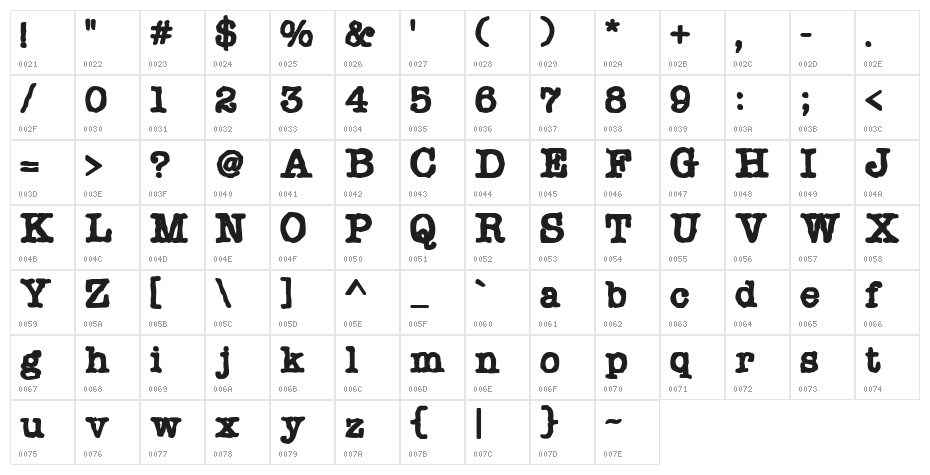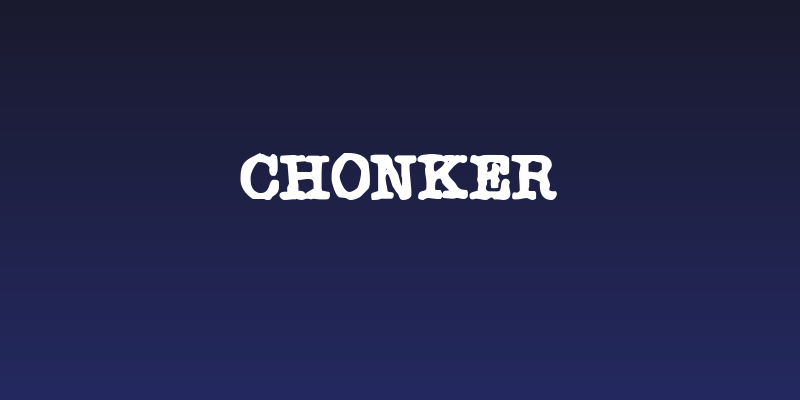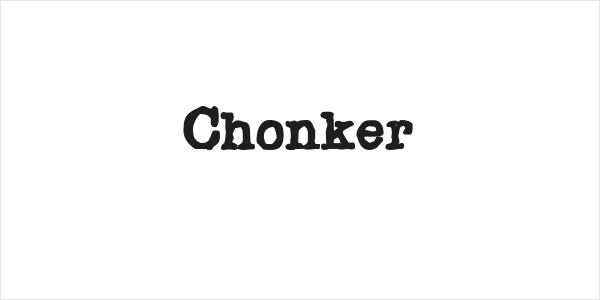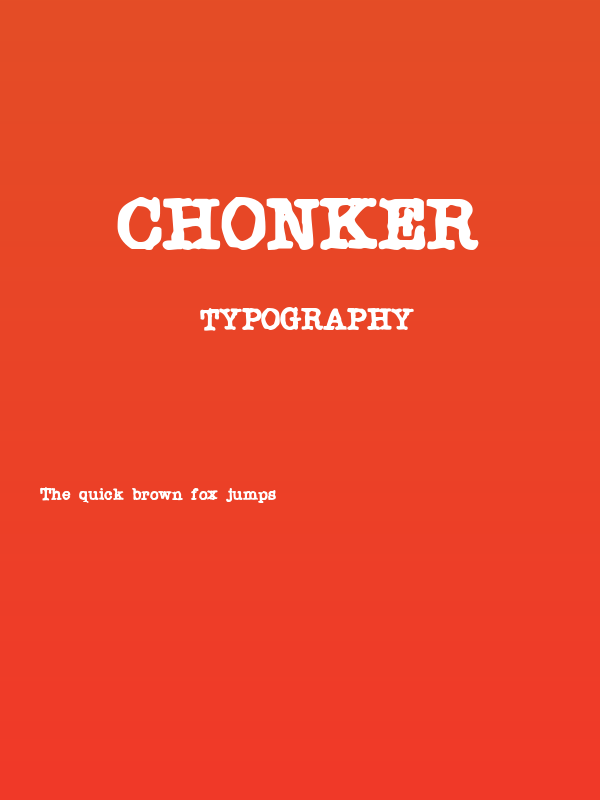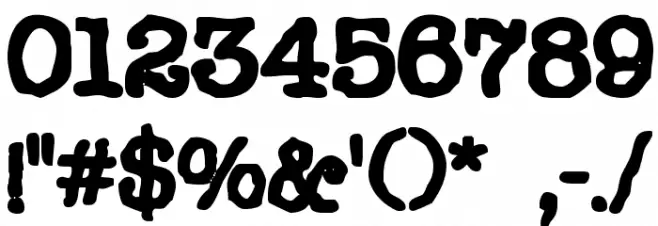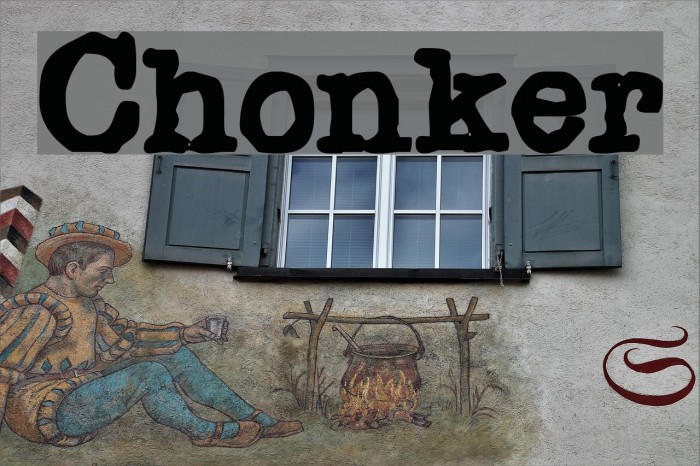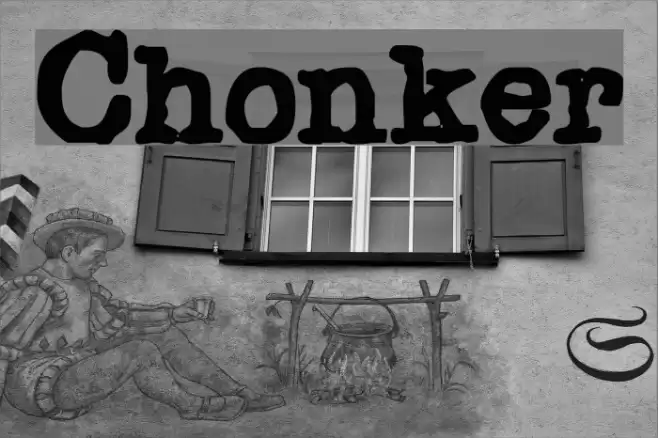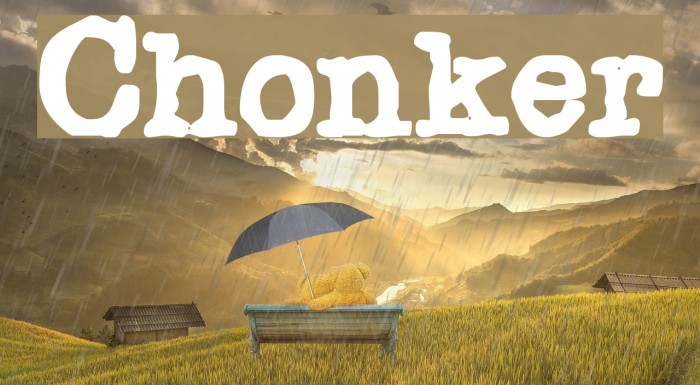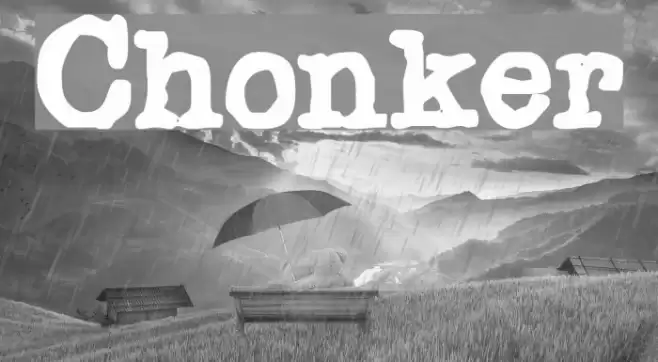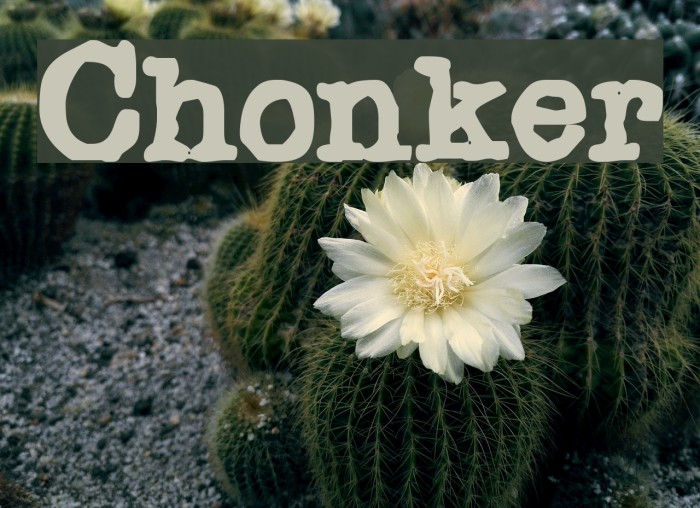
Chonker Font
✎ Typewriter
| Estilo geral | Playful, Whimsical |
| Projetos propostos | Perfect for children's books, playful branding, posters, and creative projects that require a fun and bold typeface. |